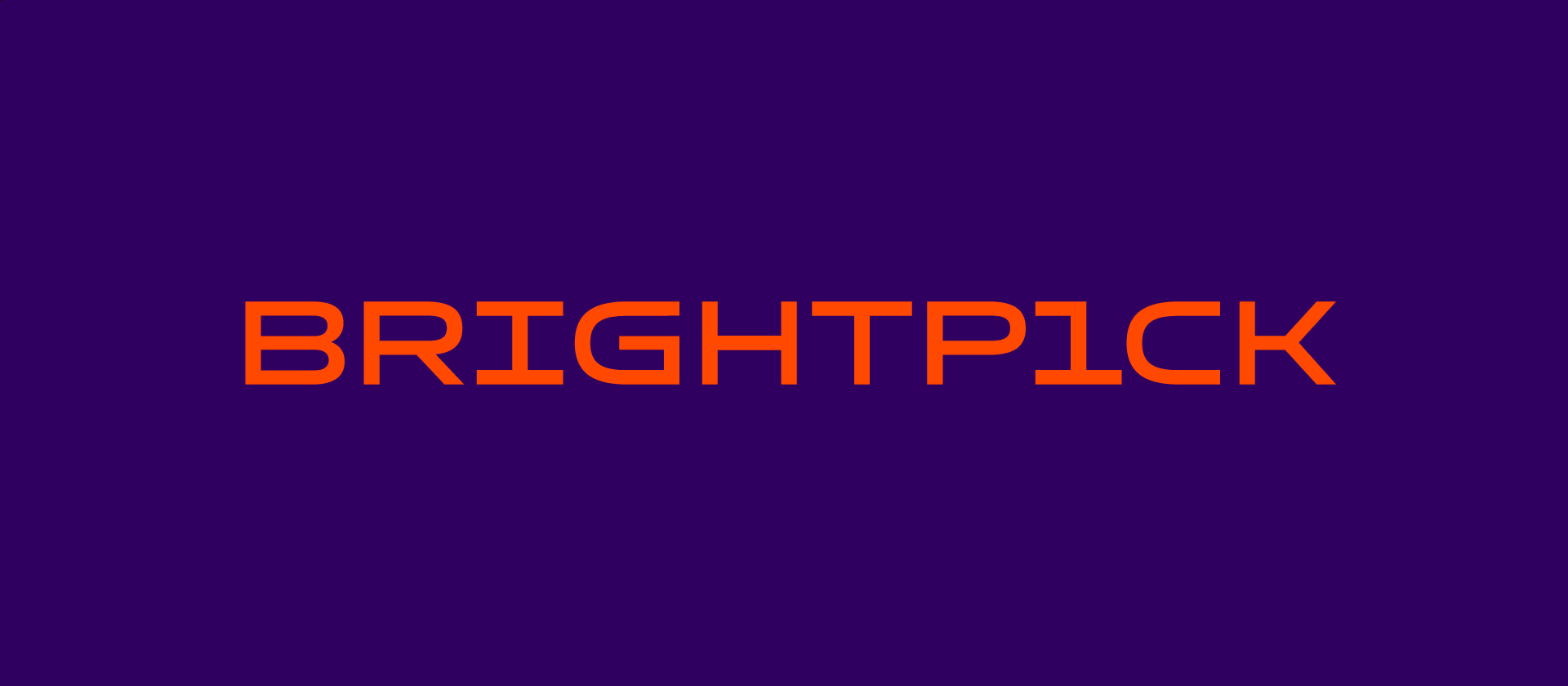
Brightpick
Písmo na mieru2023
Písmo Brightpick vytvorené na mieru špeciálne pre použitie vo vizuálnej identite slovenskej technologickej spoločnosti Brightpick, ktorá ponúka celosvetovo najefektívnejšie riešenie automatizácie skladov pre e-commerce, vrátane potravín.
Sans-serifové monolineárne písmo disponuje širokými proporciami, jeho konštrukcia, ktorá kombinuje ostré a zaoblené spájanie ťahov, je inspirovaná automatizovaným pohybom robotov v priestore.